字体的造型,是指关于字体的外观形态、比例结构与笔画组成的设计环节。这个环节是整个字体设计过程的基础环节,目的在于设计字体的平面外观形态与塑造字体的初步性格归属,是字体的表现环节的基础,其重要性不言而喻。
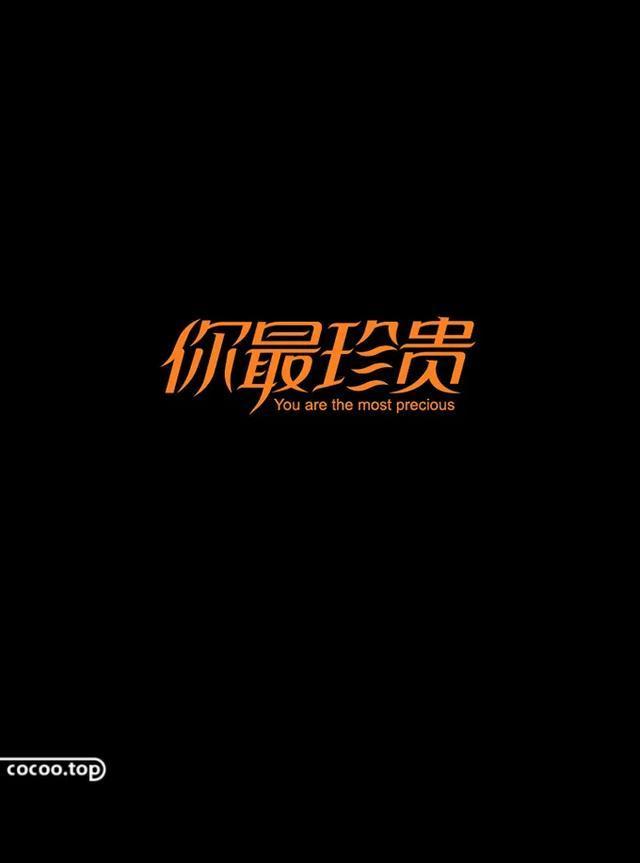
严谨刻画
时至今日,刻画早已不是字面的简单意思,而是作为字体设计中一种非常重要的字体造型手法的定义存在,主要是指对字体的比例长度与宽度的比例,结构、笔画、距离、间距、行距,进行严谨精确的造型,以确保字体的视觉效果达到精准。
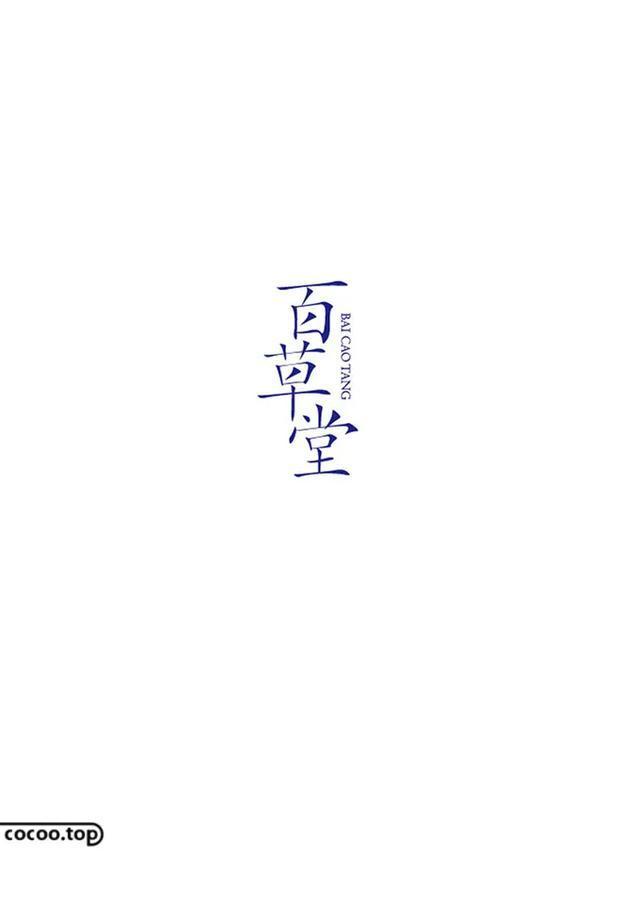
在刻画的手法中,字体的长宽比例是基础,也是确定字体基本形式外观的前提,在此基础上结构与笔画成为唇齿相依、相互制约的两个部分,结构的松与紧制约着笔画的粗与细,笔画的直与曲左右着结构的刚与柔。同时,要兼顾不同文字之间笔画多与少、结构繁与简的区别,从细节上对字体进行精确调整。
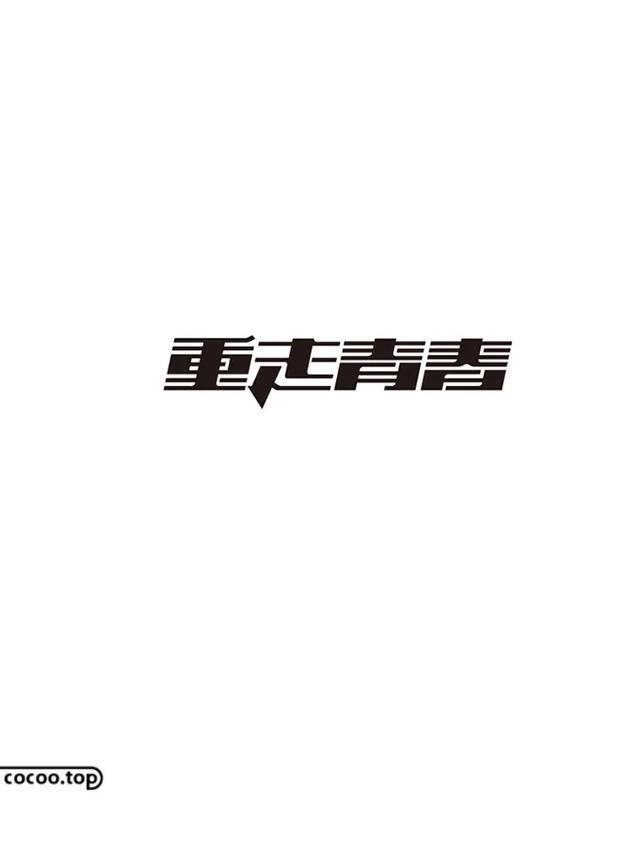
多样形变
形变是指重新塑造或改变字体外观形态的造型手法。众所周知,汉字字体的基本外观形态是方形或者矩形,然而拉丁字母中的单个字母形态虽有矩形圆形、三角形、梯形等多种形状,但其基本组合序列也为矩形形态。有时候需要更多样的字体外观形态来满足不同的设计需求,其造型变化主要分为:
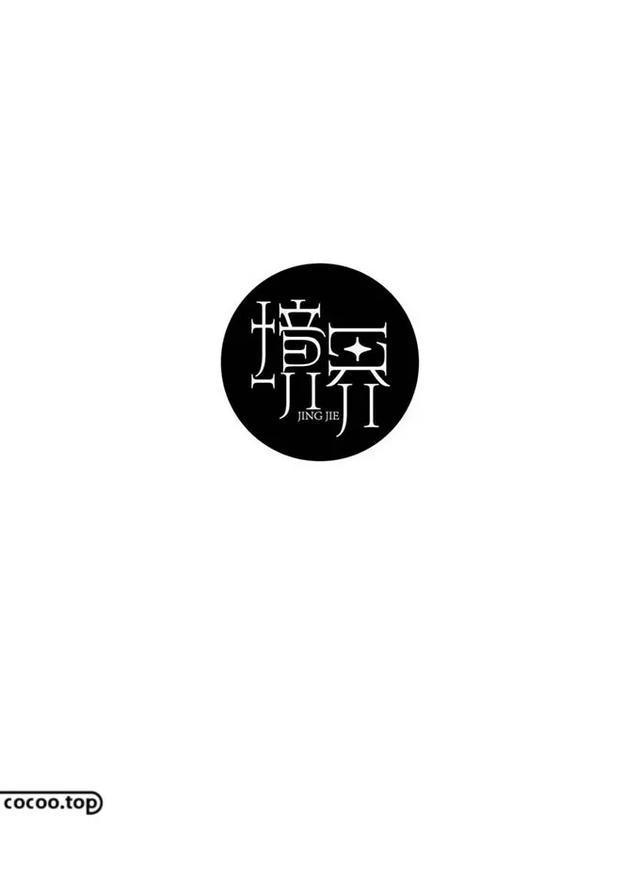
●字体的整体形态变化,主要是指将字体或字体组合塑造或改变为非基本形态以外的任意的平直、弯曲不规则或混搭的多元形态,在此基础上结合不同的表现方式,塑造独一无二的字体形象与性格情绪。
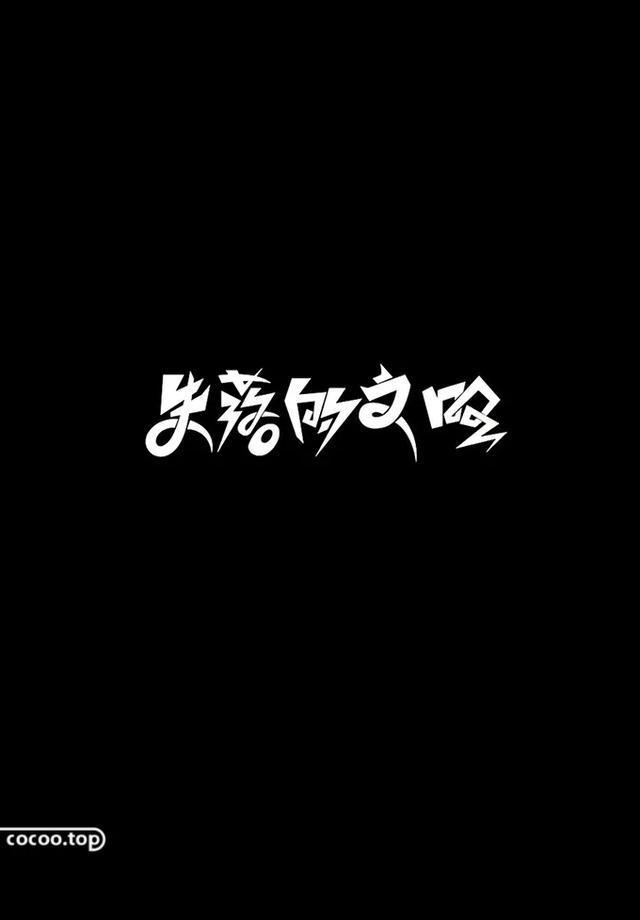
●字体的局部形态变化,主要指笔画端点、转角与装饰线的造型。其中,笔画的端点可以是平直或弯曲、尖突或圆润、上翘或下行等多元形态;笔画的转角可为尖角、圆角、平角、凹陷、突出等转角形态,以配合不同的字体笔画形态;装饰线的设计则可根据字体的外观形态需求设计长或短、粗或细、平直或弯曲、简单或复杂、柔软或刚劲等方面的造型变化。
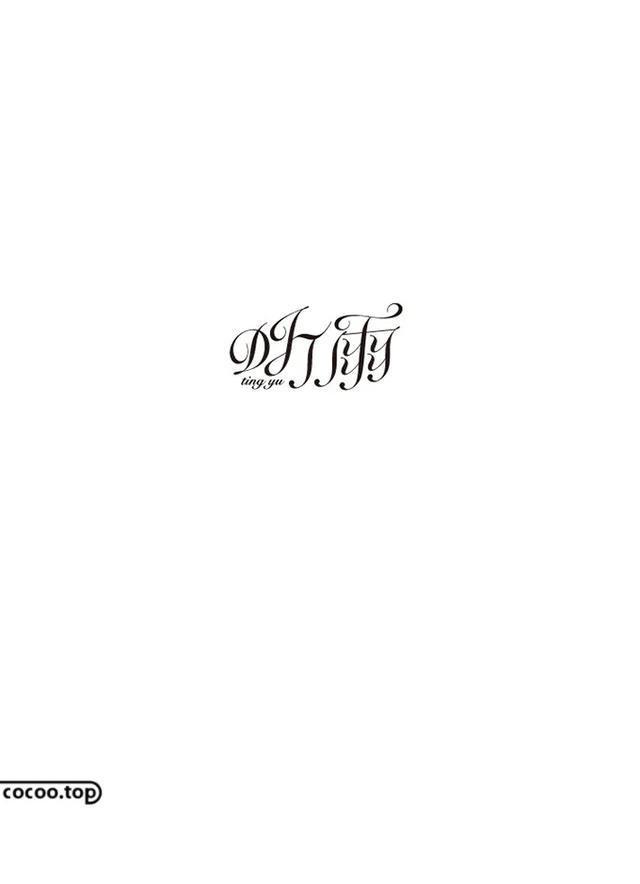
从容简略
汉字的组成单位是笔画,每一个汉字都是由笔画组成,区别在于笔画的多或少。汉字字体有的可以简单到只有寥寥几笔,有的字体的笔画则可以达到几十画之多。汉字的这个特点使得我们在设计的时候需要采用简略的设计手法,使不同笔画数量的字体组合在一起的时候在视觉上更加和谐、均衡。
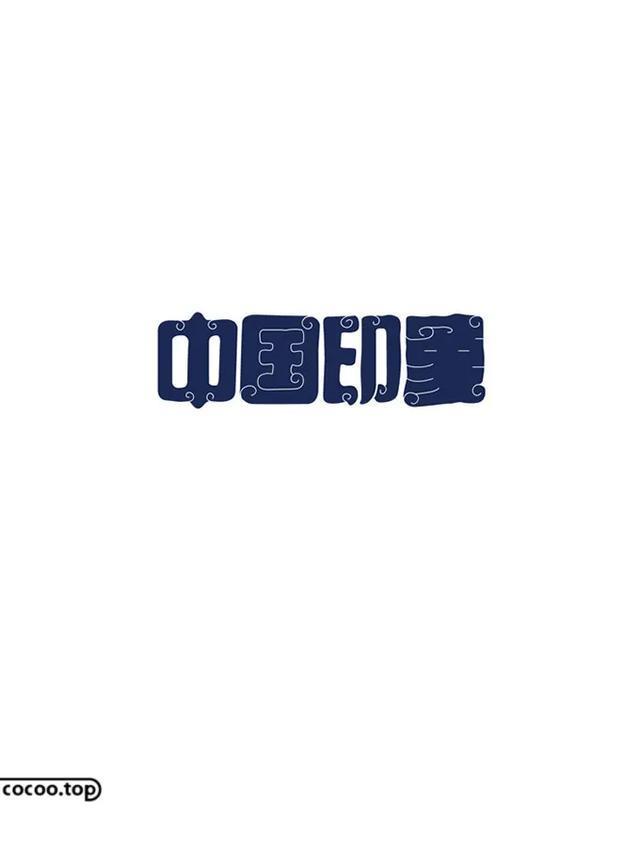
简略是指在字体设计时,有意识地对字体的笔画进行简化或省略,使字体的结构更加简约紧凑,笔画的布局更加科学、合理,最终使个体能够更好地适应全体。同时,被简略过后的字体更加具有设计的现代感,其简约的结构与时尚的外观能够更好地适应多种表现形式的需求。
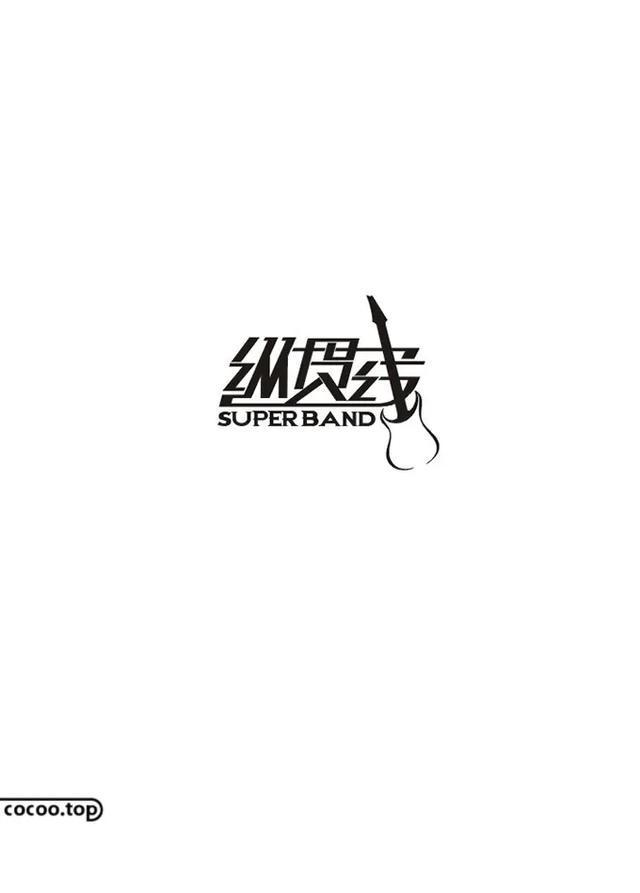
高明连接
连接是字体设计中一种常用的造型手法,主要应用在组合文字的设计中。连接能够加强组合文字的整体性和流畅性,使组合文字更加具有设计个性与艺术表现力,强化文字语意的贯彻与理解。连接主要分为:
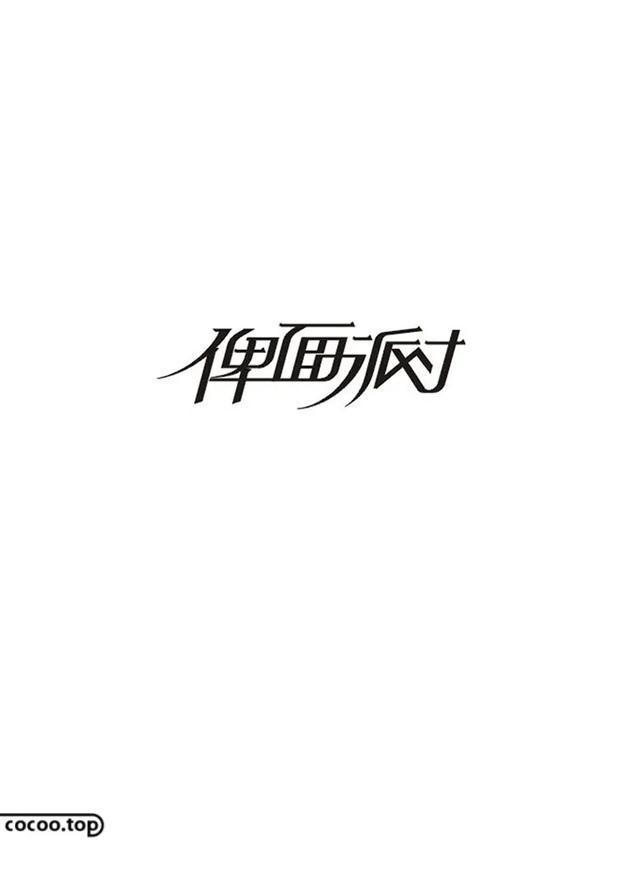
●字外连接,是指在组合文字之间对相邻字体进行连接,字外连接需要根据笔画的形状与字体的结构巧妙地选择连接的位置与方式,绝非见到笔画就去连接,同时连接线的设计需完全服从于字体的风格形式。
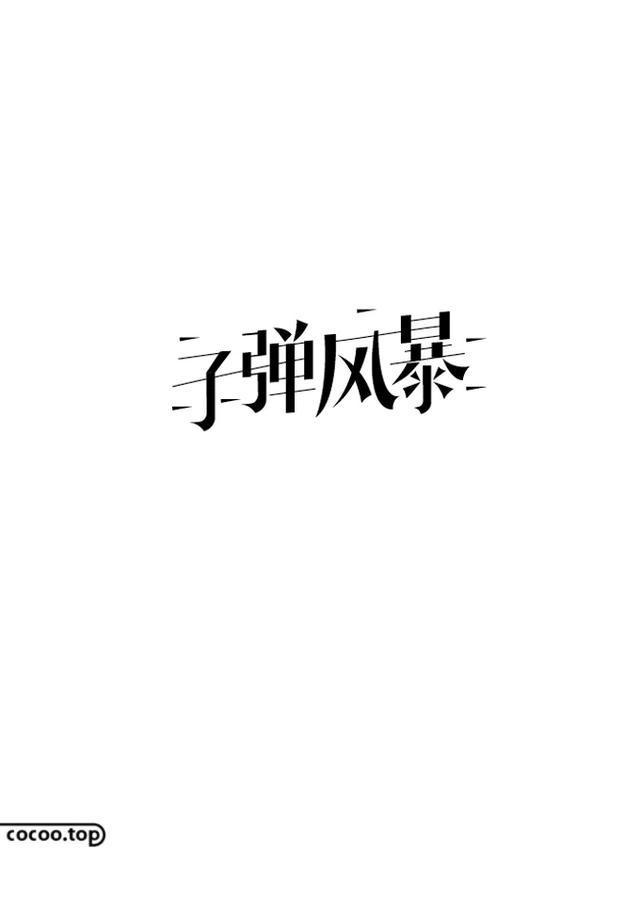
●字内连接,是指对字体内部的笔画进行的连接设计,通过对字体相邻笔画之间的连接,形成新的笔画造型从而在一定程度上改变字体形状,赋予字体更多的设计个性。连接应该要做到适可而止、张弛有度。
大胆再造
在保留已有字体风格特征的基础上,采用添加、减少或者置换的方式设计字体,是一种实用易学的字体造型手法。再造的手法,除了字体的内容外几乎没有限制,只要能实现字体设计的手法都可运用。例如:文字的创意重构、几何图形代替笔画的再造组合、正负空间的巧妙应用等。
个性重组
有意识地将两种或两种以上不同风格的字形组合搭配一起,或是在单个字体中置入不同形态的笔画类型。重组是基于字体形态对比与调和的设计法则。运用好重组造型手法,关键在于处理好字体形态间的对比与调和、变化与统一。例如:利用相同的色彩、相同的笔画形态、肌理进行调和等。
此外,重组后的字体一定要确保其识别性,因此在重组过程中要细致分析字体笔画的特点,特别是在使用不同类型的文字进行重组时要作出必要的改变和牺牲,确保字体的完整性和独特性。
磅礴绘写
书法以其多样的字体形态与浓厚的传统气韵,在字体的造型中借鉴书法的书写手法与规律,可以让字体产生更多的形态变化丰富字体的视觉效果。所谓绘写,意思是此种字体的造型手法主要包括绘和写两方面。
●书法字体表面虽为书写,但其中却包含了不少绘画的成分,因此有书画同源之说。绘写的第一种方法是将已经设计好的基本外观形态与笔画结构的字体,使用书法手法在相应材质上绘写出来,在保证字体结构与笔画完整性与严密性的基础上,将书法的磅礴气韵与书写肌理融入字体之中。
●绘写的第二方面是根据设计需求利用不同的绘制工具与表现载体直接绘写风格多样的个性手绘字体,可以是笔的慢写,也可以是刷的快涂,可以是简单的轻松随意,也可以是厚重的粗放狂野。
图文互动
图文互动,是指字体设计中文字图形化的造型手法,这种手法可以让字体与图形之间形成巧妙的互动关系,让字体的形态更加生动,意思更加明确。图文互动的手法,可以大致分为以下几种:
●首先,在充分理解字意的基础上,设计与文字内容相关的图形符号并将其置换已有字体中的某个笔画或部分字体,或是和字体进行巧妙地组合,这是图文互动表达最为简单易学的手法。
●其次,字体的完全图形化设计,意思是将字体全部用图形进行表现,这种手法需要同时考虑图形之间在风格形态上的统一性与图形和字体之间的适合性。
●再次,抽象图形的运用。在设计中重点考虑抽象图形与字体笔画、结构的配置关系,让抽象图形能够完全融入字体之中,成为字体不可或缺的组成部分,这也是图文互动手法最难也是最不容易把握的表达层次,需要大量的设计实践积累方可实现。
妙笔生花
有针对性地选择单个字体或组合字体中某一具有含义表达的代表性的笔画进行不同于字体本身的造型变化,使其产生与字体本身完全不同的形态,在整体字体中起到画龙点睛的作用。
例如:平直中的弯曲、纤细中的粗壮、光滑中的斑驳、平面中的立体、寻常中的突变、粗犷中的细腻,也许看似毫不相关,却能在设计的力量中相互包容、实现共存。字体识别
上述的字体的造型手法并非是完全的独立使用,在很多的时候都是两种或者多种手法共同作用完成字体的造型,因此在学习和使用的过程中应该将这些手法有机结合、共同思考。